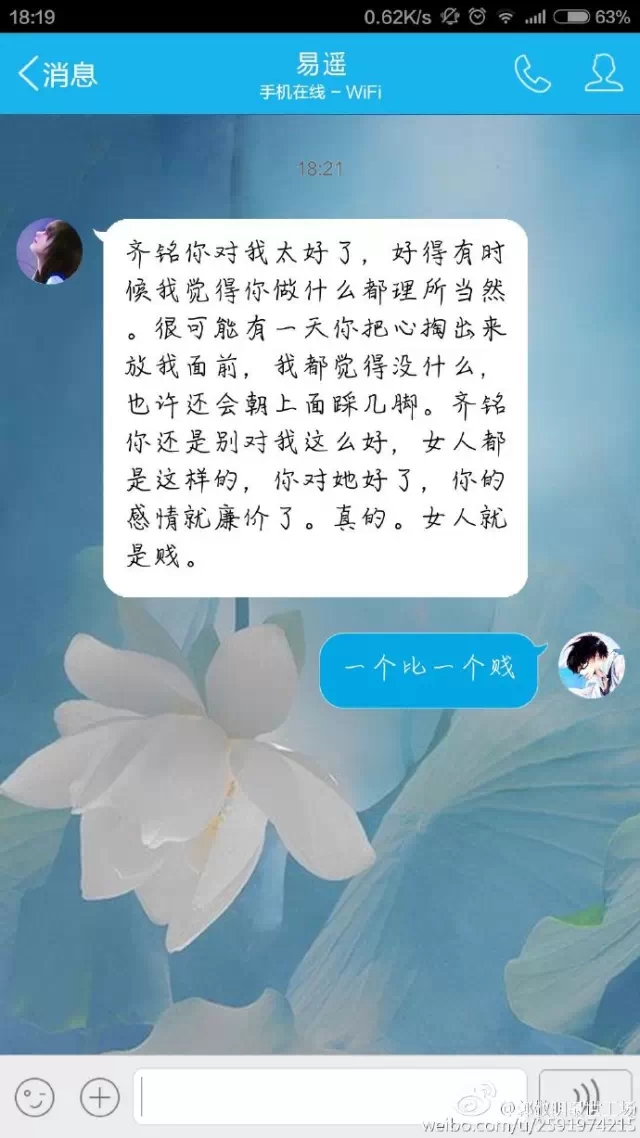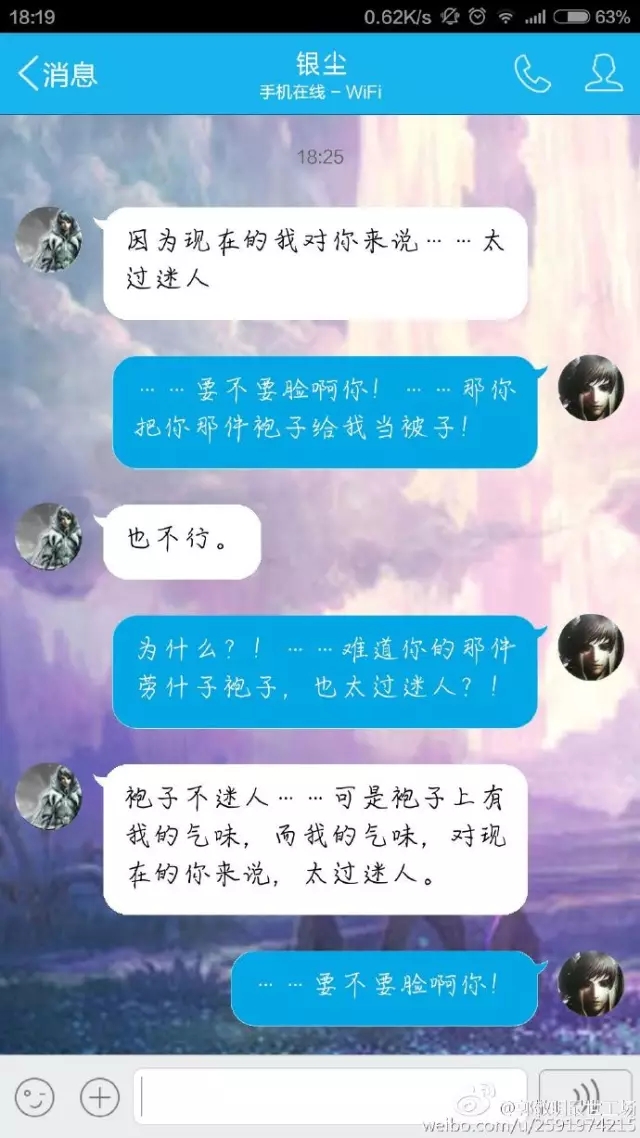
郭敬明体亮相上海国际刺青极限设计展
导语当手机QQ聊天写着跟“小四”如出一撤的文字会发生什么?日前,汉仪公司邀请著名青春文学作家郭敬明亲手写就“汉仪郭敬明体”,看不懂啥意思?科学解释就是通过先进的技术,在电脑上完美呈现郭敬明的手写字体风韵,形成字库。看到这,你的手是不是都不自觉的轻盈了起来?该字体已于4月29日在手机QQ上线发布,目前小米主题商店、SOGOU输入法、OPPO手机、酷派手机、91桌面等移动端平台均可下载到“汉仪郭敬明体”和“郭敬...
当手机QQ聊天写着跟“小四”如出一撤的文字会发生什么?日前,汉仪公司邀请著名青春文学作家郭敬明亲手写就“汉仪郭敬明体”,看不懂啥意思?科学解释就是通过先进的技术,在电脑上完美呈现郭敬明的手写字体风韵,形成字库。
看到这,你的手是不是都不自觉的轻盈了起来?
该字体已于4月29日在手机QQ上线发布,目前小米主题商店、SOGOU输入法、OPPO手机、酷派手机、91桌面等移动端平台均可下载到“汉仪郭敬明体”和“郭敬明小时代特别版”。为广大的郭敬明粉丝提供了亲近偶像的机会,同时汉仪字库也通过明星定制字体的方式,引导大众用户对于字体文化的关注。